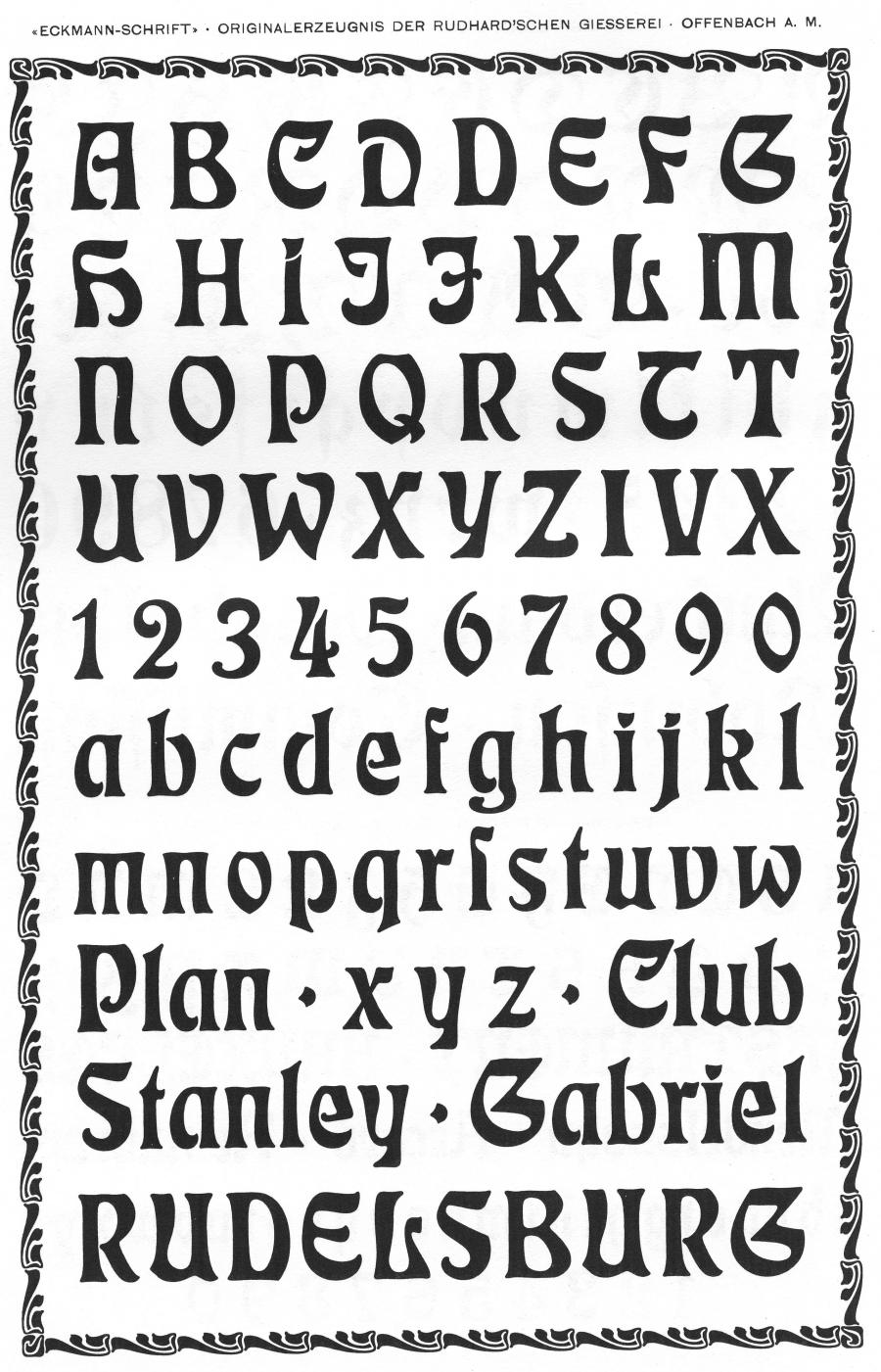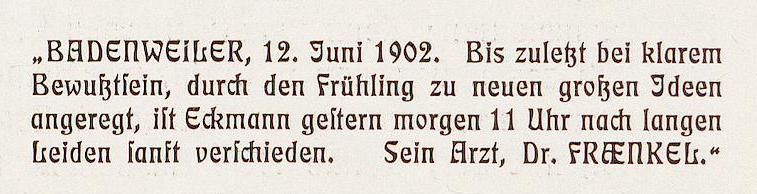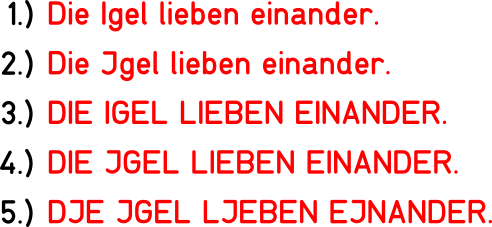
Verschiedene I-Schreibungen in handschriftlichem Deutsch
1. 1. Welche Schreibweisen im untenstehenden Bild findet Ihr in einem handschriftlichen deutschen Text akzeptabel? Nota bene: Es geht um die Schreibweise allgemein, nicht um die konkrete Lesbarkeit im Beispielbild!
• Schreibung 1
34%
• Schreibung 2
22%
• Schreibung 3
28%
• Schreibung 4
11%
• Schreibung 5
2%
Der Zusammenhang: Andernthreads fiel mir das Folgende ein:
Mir ist in dem Zusammenhang übrigens schon länger aufgefallen, dass Deutsche, wenn sie handschriftlich in reinen Versalien schreiben, beim I und J besondere Regeln beachten:
• Das I kann J-Form haben, jedoch nur am Wortbeginn; ansonsten hat es stets I-Form;
• ein I in J-Form hat stets einen Querbalken oben, jedoch nie eine Unterlänge;
• das J kann dagegen unten aus der Zeile herausragen und braucht auch keinen Querbalken; und:
• ein Querzug durch den Schaft eines J mit Querbalken und ohne Unterlänge kann nur beim I gesetzt werden; beim J steht er nur, wenn es Unterlänge hat.
Könnt Ihr diese Beobachtungen bestätigen?
Das Problem finde ich, wie geschrieben, schon länger (schon seit der Grundschule! :huhu:) interessant, möchte aber den Wallenstein-Thread nicht kapern und finde, dass Daten dazu hilfreich wären. Namentlich fand Oliver Weiß die J-förmige Schreibung des I antiquiert, was in veröffentlichten Texten zweifellos zutrifft, meiner Erfahrung nach jedoch nicht in der alltäglichen Handschrift.
Ich weiß nicht, wie sich »akzeptabel« in diesem Zusammenhang definiert.
Letztlich kommen die Formen ja aus den (im 20. Jahrhundert) gelernten Handschriften verbundene Schreibschrift bzw. Blockschrift. Versal-Schreibschrift macht aber eigentlich wenig Sinn. Versal-Blockschrift hingegen schon. Dass sich über die Jahre dann generelle oder kontextspezifische Mischformen ausprägen, verwundert aber auch nicht.
Ich weiß nicht, wie sich »akzeptabel« in diesem Zusammenhang definiert.
Das ist ein Kriterium, das ich aus der experimentellen Linguistik gemopst habe. Akzeptabel bedeutet, es wird verstanden und fällt nicht als falsch auf.
Ich habe in meiner Sammlung von Schriftvorlagen auch Figutenverzeichnisse, welche alle drei Formen enthalten, So enthalten einige Figurenverzeichnisse sowohl ein großes J mit Unterlänge für den Buchstaben J mit Deckstrich und Unterlänge für den Buchstaben J selbst am Wortanfang, dann eine J-ähnliche Form für den Buchstaben I am Wortanfang, ohne Unterlänge, und dann das gerade I für das Wortinnere in Versalschrift, Selbst ein J mit nur kleinerer Unterlänge und ohne Decksstrich für den Buchstaben J innerhalb Versal geschriebener Worte habe ich gesehen, der dann im Text nicht so breite Lücken reißen soll
Das J-ähnliche Anfangs-I gibt es übrigens auch in den deutschen Fibelschriften, die J-Form im Süden, die I Form im Norden. Ich hatte meine diesbezüglichen Schriften ja noch einmal für eine Schul-Arbeitsblatt-Software überarbeitet. Hier hatte ich dann bei der Nord-Version der Schrift dass hier es bei der Fett-Umschaltung Probleme gab, nur weil Nord im Schriftnamen steht, bei der "Sued" Version hingegen nicht. Ich hatte hier sogar Kontakt zu Elsner+Flake aufgenommen, weil ich in einer derer Fonts das gleiche Problem gefunden hatte. Sie konnten diesen Bug bestätigen, eine Lösung konnten sie auch nicht finden, geholfen hat dann einer meiner Tippfehler, nachdem ich Nord durch Nurd ersetzte, war der Fehler weg :-)
Das J-ähnliche Anfangs-I gibt es übrigens auch in den deutschen Fibelschriften
Genau das war den Anfang meines Staunens! Wir hatten im ersten Schuljahr eine Fibel mit J-I und im Klassenzimmer eine Druckbuchstabentafel mit I-I. Als ich das bemerkte, begann ich, mich auch theoretisch für Schrift und ihr Verhältnis zur Sprache zu interessieren.
In einem handschriftlichen, deutschen (?) Text finde ich alle akzeptabel im Sinne von lesbar. Beim letzten Beispiel könnte ich mir allerdings vorstellen, dass das so in dieser Reinform nicht oder selten vorkommt. Ich denke beim Schreiben wird man automatisch Unterschiede machen.
Abgelöst von der Wallenstein-Debatte hätte ich aber noch gerne andere Formen wie das Bahnschienen- oder Stahlträger-I ⬅️ gesehen.
Vorletzte Variante würde ich auch mal gerne in freier Wildbahn sehen bzw. ob das überhaupt jemand so praktiziert.
Meine Aussagen beziehen sich auf handgeschriebene Texte, Satz-Handschriften folgen m. E. anderen Prämissen und ich halte das auch legitim.
Dass das Stahlträger-I als akzeptabel gesehen wird, hielt ich für ausgemacht. Im Deutschen ist das doch einfach eine Nebenform des I-I, oder nicht? Im amerikanischen Comics-Versallettering wird hier allerdings ein Unterschied gemacht: Das Stahlträger-I steht nur für das Wort I und in Großbuchstaben-Abkürzungen; in allen anderen Fällen steht das einfache Strich-I.
Vorletzte Variante würde ich auch mal gerne in freier Wildbahn sehen
So ähnlich lief das bei mir auch, Hier war es unser Klassenlehrer, der irgendwann abseits vom offiziellen Lehrplan meinte, wir sollten auch die Briefe unserer Eltern und Großeltern lesen können, und uns in nur 2 Schulstunden die deutsche Kurrent näher gebracht hatte.  Wo wir eigentlich nicht zu bändigenden St-Paulianer sonst es ihm viel zu schwer gemacht haben, waren wir jetzt mit viel interesse bei der Sache.  Und wo wir so dann eine Klassen-Geheimschrift hatten, haben wir dann auch noch einen Blick über den Gartenzaun gewagt, und, da mein Bankgenosse ein Bulgare war, auch einen grundlegenden Einblick ins Kyillische gewagt. Wahrscheinlich bin ich nur deshalb auf dieser Seite hier?